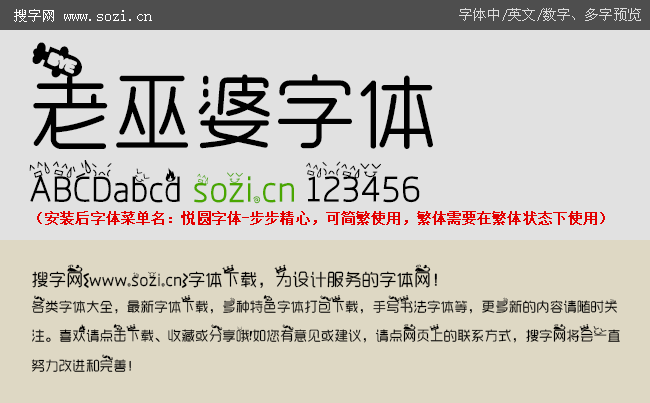
老巫婆字體
搜字網(wǎng)給大家提供一款老巫婆字體手機(jī)中文字體下載。這款手機(jī)字體是以圓體字體為原形,字體裝飾了可愛(ài)的卡通圖案。在具備圓字體清晰端正的風(fēng)格同時(shí),卡通味也特別濃,是一款非?蓯(ài)的卡通字體,特別適合喜歡手機(jī)字體個(gè)性一些的朋友在手機(jī)上安裝使用。